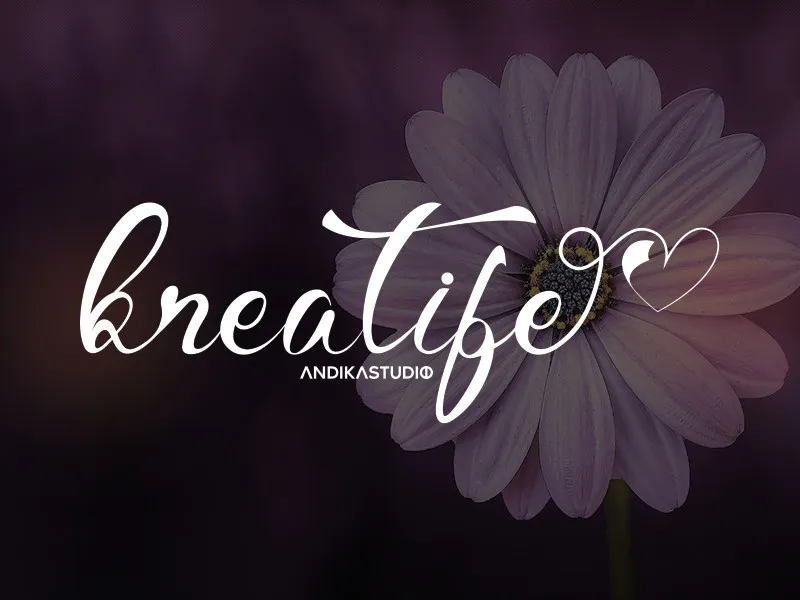
Kreatife Script Font – Download Grátis
Esta fonte chamada Kreatife Script Font é perfeita para quem quer dar ao seu projeto um toque elegante e sofisticado. Inspirada na arte do xilográfico, essa fonte permite criar designs únicos e imprimíveis de alta qualidade. Através dela, você pode expressar seus pensamentos de maneira única em materiais impressos ou até mesmo em aplicativos digitais. Sua usabilidade versátil faz com que seja uma escolha ideal para designers, artistas gráficos e qualquer pessoa que busque uma fonte perfeita para personalizar seus trabalhos artísticos. O designer andikastudio criou essa fonte com os detalhes e nuances precisos necessários para criar texturas variadas, desde códigos de estilo até capítulos e headlines. Para uso comercial, é preciso entrar em contato diretamente através do endereço . Por enquanto, o Kreatife Script Font está disponível apenas para uso demonstrativo (demo license). Isso significa que você pode experimentar todos os recursos da fonte sem comprometer seu uso futuro. Mas se deseja incluir essa fonte em produtos comerciais ou projetos pagos, é necessário fazer uma solicitação de licenciamento separado através do email fornecido.